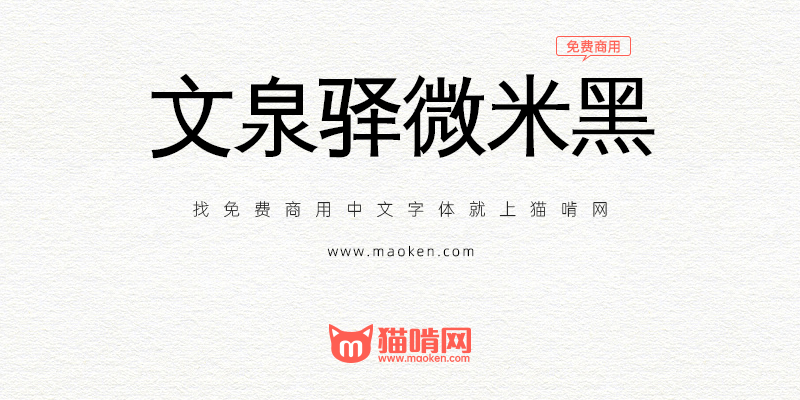
文泉驿微米黑:开源免费高清晰黑体字体,适配小尺寸显示场景
字体作者:文泉驿 (中国大陆) 字体字重:1个
文泉驿微米黑是一个”自由字体“。该字体包含了所有常用简体中文、繁体中文所需要的汉字(最新版本包含超过20932个汉字,完整覆盖GB2312/Big5以及GBK标准字符集)。该字体同时还包含了日文、韩文和其他几十种语言符号。以外,该字体还包含了高质量的Droid Sans拉丁符号和Droid Sans Mono等宽字体,并内置Hinting和Kerning信息。微米黑字体文件极小,特别使用于便携式电脑设备。
文泉驿微米黑由于是由旧版 Droid Sans Fallback 衍生的,会有「妩」显示成「妧」的 bug。
• 將新版的 Droid Sans Fallback (最後一個版本已經覆蓋擴展a區)添加來自 Droid Sans的英文數字並添加直排、連字特性,因為能力有限,漢字結構問題如設段等字未修改 再次感謝lxgw